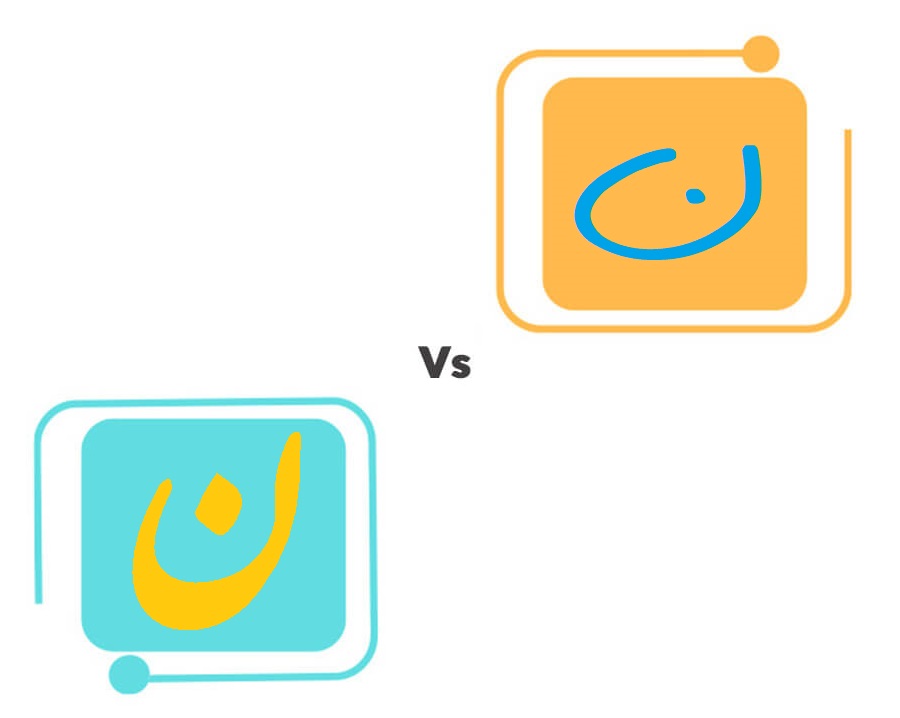
خوشنویسی و دست نویسی
خوشنویسی و دست نویسی | بیان ویژگی ها و تفاوت ها به زبان ساده
مفهومی به نام خوشنویسی و دست نویسی و یک سوال از شما دوستان. واقعا تفاوت این اصطلاحات بالا چی میتونه باشه ؟ اصلا مگه همشون یک چیز نیستن؟ اگه میخوای یک تعریف اصولی و درست از این 3 اصطلاح بالا رو داشته باشی و خیلی آسون این مفاهیم رو یاد بگیری با ما همراه باش دوست عزیز.
دست نویسی اولین قدم انسان در نوشتن
وقتی صحبت از دست نویسی میشه کاملا مشخصه که هر چیزی ائم از نوشته و علائمی که بشر با دست خودش مینوشته جزء خانواده دست نویس یا دست نویسی محسوب میشده. دست نویسی 2 ویژگی منحصر به فرد داره که ملاک تشخیص اون محسوب میشه
ویژگی های دست نویسی
اولین ویژگی خط و خانواده دست نویسی، بی قائده بودن اون هست . یعنی یک قانون کلی برای نوشتن وجود نداره. اگه بخوام با مثال واستون توضیح بدم، دست خط هر شخص جزء نوشته های دست نویس محسوب میشه و هر شخص هم قانونی و قائده ای برای نوشتن خودش داره ولی در نگاه کلی قائده ای که شامل همه دست نویس ها بشه وجود نداره
دومین ویژگی عدم وابسته بودن به ابزار هست . یعنی توی دست نویسی اینکه ابزار ما چه نوع قلمی باشه اصلا مهم نیست. یعنی تمامی نوشته هایی که با قلم های مختلف روی سطوح مختلف مثل گل، سنگ، چوب و پوست حیوانات … توسط اشخاص مختلف بدون رعایت یک قانون و قاعده کلی نوشته میشه رو می‌گیم دست نویس.
خوش نویسی قدمی برای زیبا و قائده مند نوشتن
کاملا مشخص بود که همچین اتفاقی یعنی ظهور خوشنویسی باید اتفاق می افتاد. نیاز بود تا یک قاعده کلی برای اینکه نوشته ها زیبا تر و خوانا تر بشن اجرا بشه. به بیان ساده تر خوشنویسی یعنی نوشتن با دست ولی به شرط رعایت قائده و قانون و همچنین متکی شدن به ابزار و قلمی خاص در نوشتن.
اینجا بود که خوشنویسی سبب خلق خانواده هایی چون نستعلیق ، نسخ و … مثلا در این حرف نون نستعلیق می‌تونید ببنید که ترتیب نوشتن، زاویه قلم ضخامت و اندازه‌ها دقیقا تعیین شده و برای همین در هر بار نوشتن شکل حروف تغییر نمی‌کنه حالا این توسط هر شخصی هم که با دست مینویسه و دست خط خودش رو هم داره باید رعایت بشه تا خوشنویسی محسوب بشه .
دومین ویژگی هم وابسته بودن خوشنویسی به ابزار هست. یعنی شکل حروف در نستعلیق تحت تاثیر ابزار قلم‌نی و جوهر شکل گرفته.
و در خوشنویسی چینی شکل حروف کاملا تحت تاثیر ابزار قلم مو هست.
اما اکثر دست خط‌های شخصی ربطی به ابزار خاصی ندارن و ساده نوشته میشن. الان میتونیم بگیم که با مفاهیم و ویژگی های خوشنویسی و دست نویسی آشنا و درک بهتری از اونها پیدا کردین . امیدواریم این مطلب واستون مفید بوده باشه